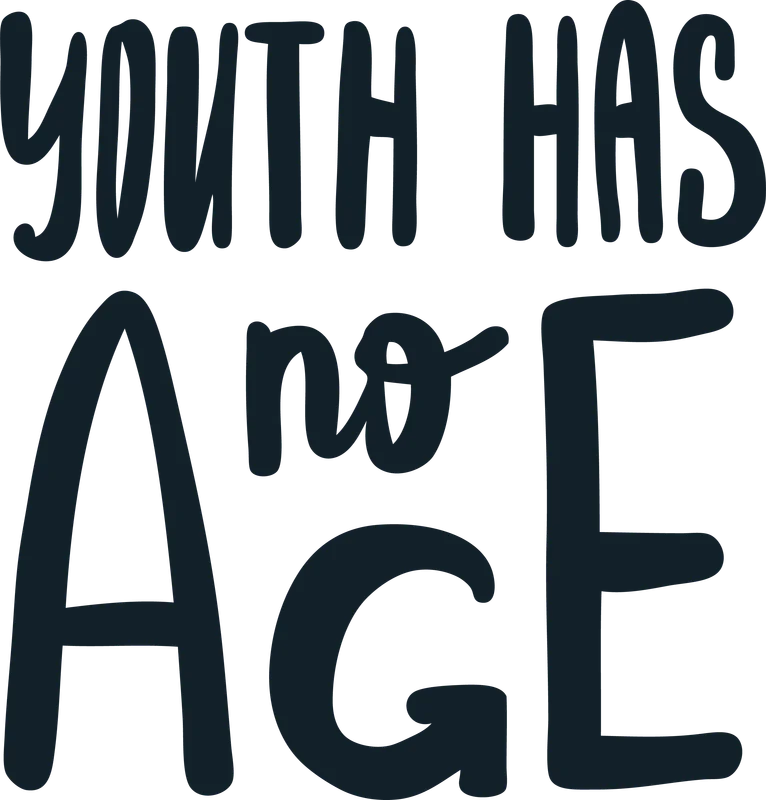
Thông điệp "Youth Has No Age" font chữ độc đáo
Thông điệp "Youth Has No Age" font chữ độc đáo — Thiết kế typography độc đáo với thông điệp "Youth Has No Age" truyền cảm hứng. Phù hợp in áo thun, túi tote, sticker. Có thể in bằng công nghệ DTF.
Trong hình có: chữ viết, thông điệp
Phong cách: flat-design · Cảm giác: cool